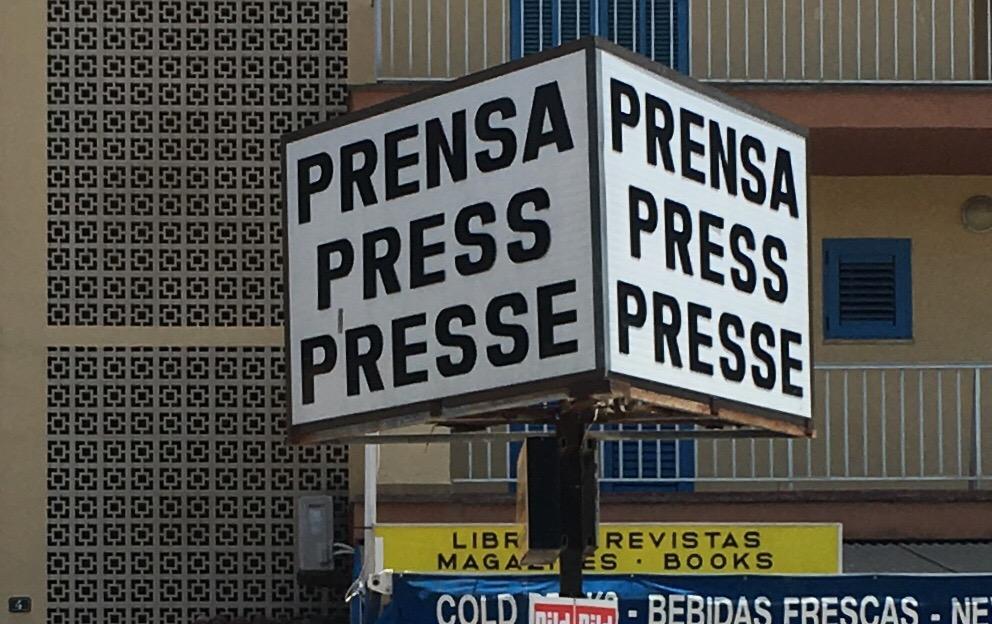
Suche die Schrift dieses Presseschildes
Ich denke dieses Schild stammt aus den 60er Jahren und das Foto ist auf Mallorca entstanden, wir würden gerne eine solche Tafel nachbauen und suchen deshalb nach dieser Schrift oder einer ähnlichen. Vielen Dank
Das ist viel zu unausgeglichen für eine Satzschrift und wurde also selbst sehr wahrscheinlich handgemacht: da hat wer für jeden Buchstaben eine Schablone gebastelt und die dann vervielfältigt, z.B. 10 × für das S. Wenn du das Schild möglichst authentisch reproduzieren möchtest, machst du es genau so.